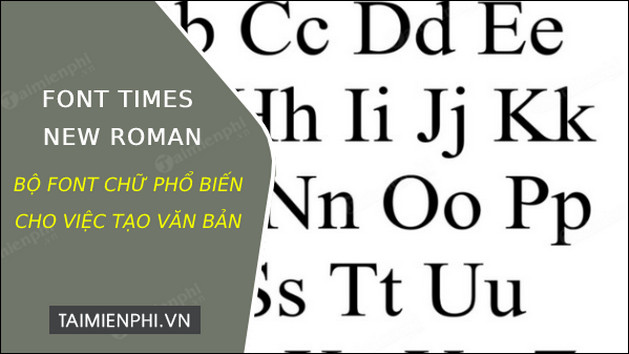
Font Times New Roman
Font Times New Roman, phông chữ kinh điển từ năm 1932, là lựa chọn lý tưởng cho các tài liệu văn phòng và học thuật. Với thiết kế tinh tế và dễ đọc, nó mang đến sự chuyên nghiệp cho mọi văn bản. Hãy tải ngay Font Times New Roman để nâng cao chất lượng nội dung của bạn
1. Giới thiệu bộ font chữ Times New Roman
Font Times New Roman là phông chữ kiểu serif ra đời cách nay đã khá lâu và được sử dụng phổ biến ở khắp nơi không chỉ riêng Việt Nam. Đặc biệt từ năm 2004 Bộ ngoại giao Hoa Kỳ đã ra tuyên bố rằng tất cả các văn kiện ngoại giao Mỹ sẽ bắt buộc phải sử dụng font chữ Times New Roman thay vì font chữ Courier New như trước đó.
Font chữ tạo văn bản và nhập dữ liệu phổ biến
Ở Việt Nam cũng vậy, font Times New Roman cũng được sử dụng nhiều trong các văn bản hành chính nhờ thiết kế rõ ràng, đơn giản và đẹp mắt. Vì vậy có thể khẳng định rằng đa phần người sử dụng máy tính đều tải Times New Roman và cài đặt như một font chữ chính khi soạn thảo văn bản của mình.
2. Sử dụng Font Times New Roman mang đến những lợi ích gì?
- Phông chữ Times New Roman được thiết kế để dễ đọc trên giấy và màn hình, giúp người đọc có trải nghiệm đọc tốt hơn.
- Font này thường được sử dụng trong văn bản chính thức, văn phòng, và công việc học thuật, tạo ra ấn tượng chuyên nghiệp.
- Font Times New Roman in ấn rõ ràng và sắc nét trên nhiều loại giấy và máy in.
- Loại Font này phổ biến và được hỗ trợ trên hầu hết các hệ điều hành và ứng dụng văn bản, giúp đảm bảo tính tương thích và dễ dàng chia sẻ tài liệu.
3. Những loại phông chữ tương tự Font Times New Roman
Ngoài ra, nếu bạn muốn có một font chữ có nhiều ưu điểm như Times New Roman nhưng có ít "cạnh" hơn, thì font chữ UTM Avo cũng sẽ là một sự lựa chọn tuyệt vời dành cho bạn, Font chữ UTM Avo mang lại cho người sử dụng một cảm giác nhẹ nhàng, mềm mại và tròn trịa hơn trong khi Times New Roman có vẻ cứng rắn và nghiêm túc.